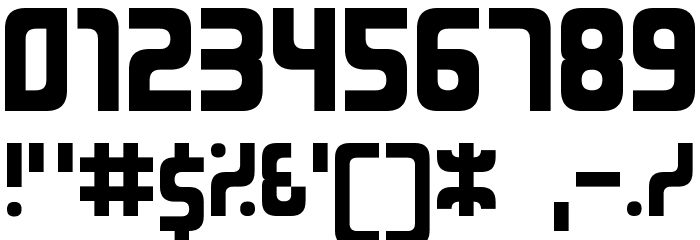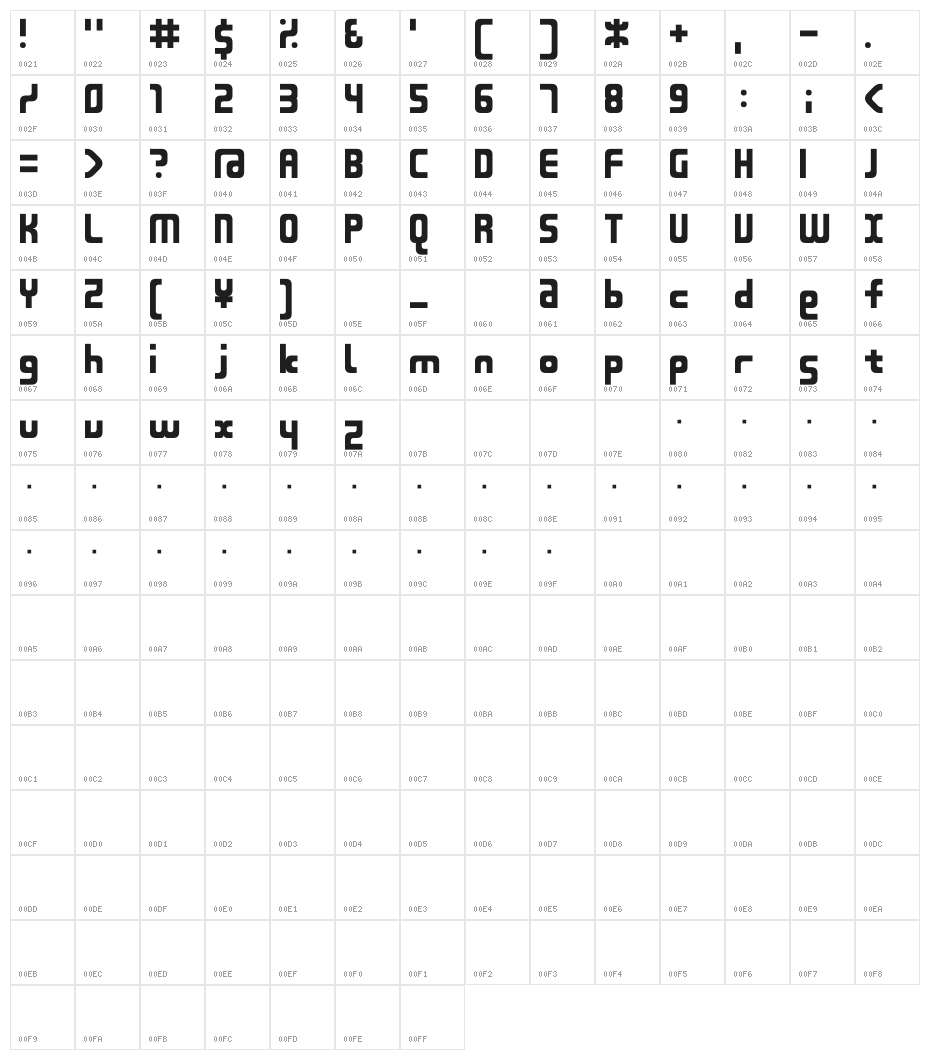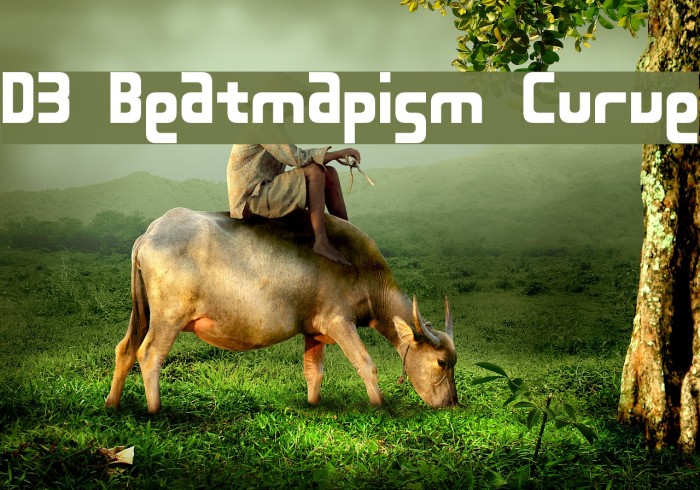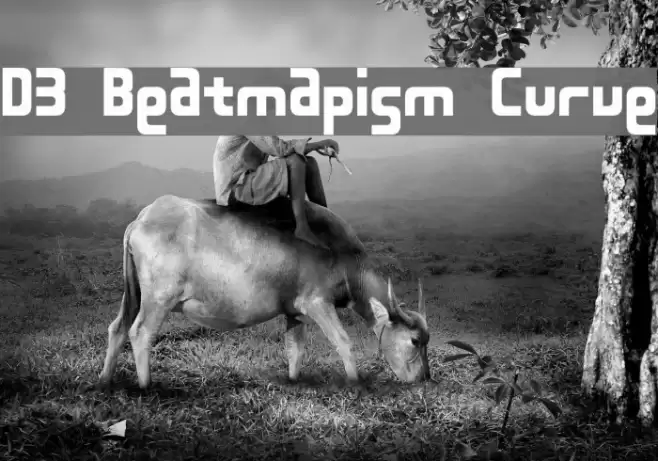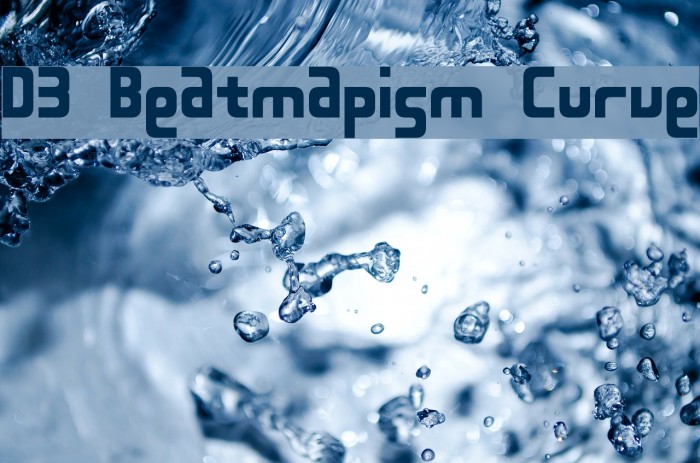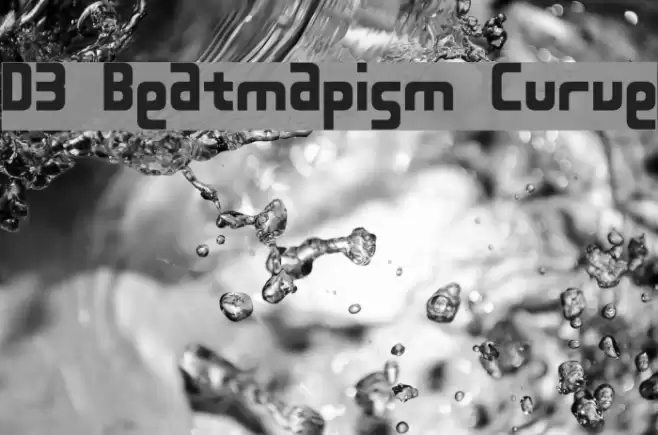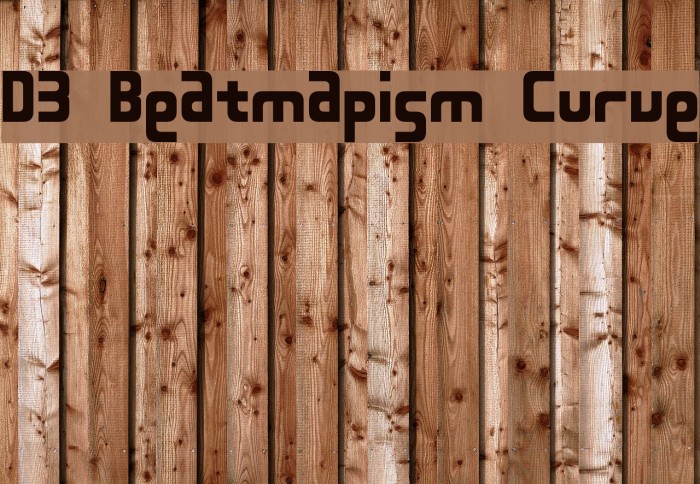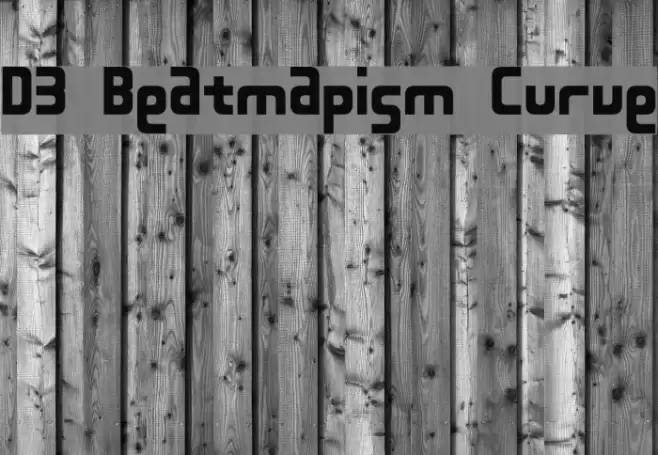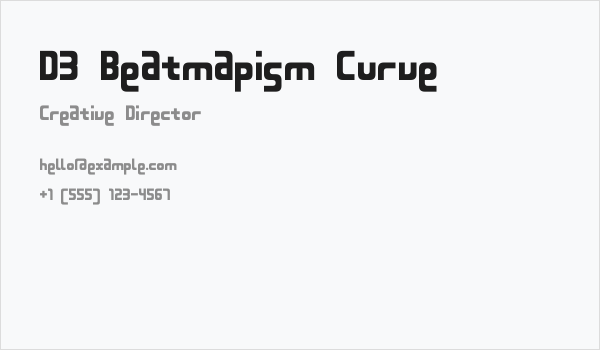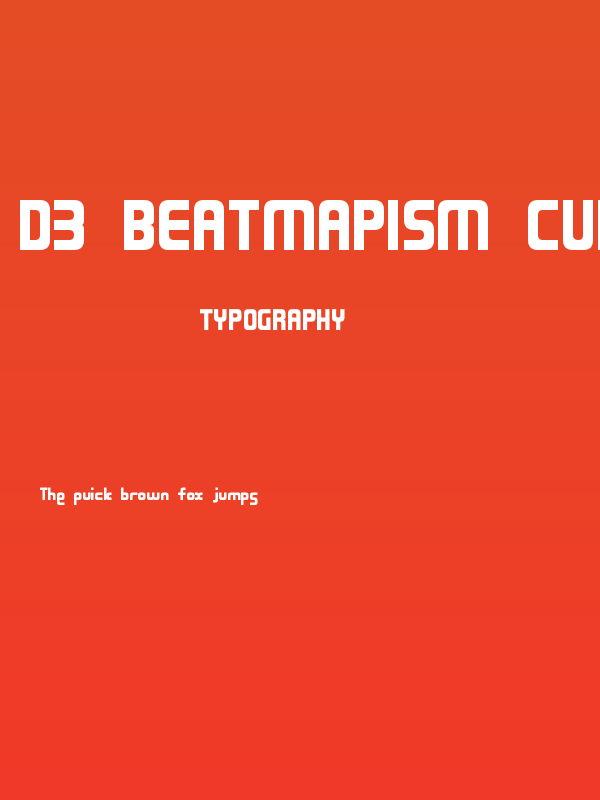
D3 Beatmapism Curve Font
| Anwendungsfall | Headlines, Logos, Digital Interfaces |
| Vorgeschlagene Projekte | Ideal for branding, digital interfaces, posters, and modern advertising campaigns. |